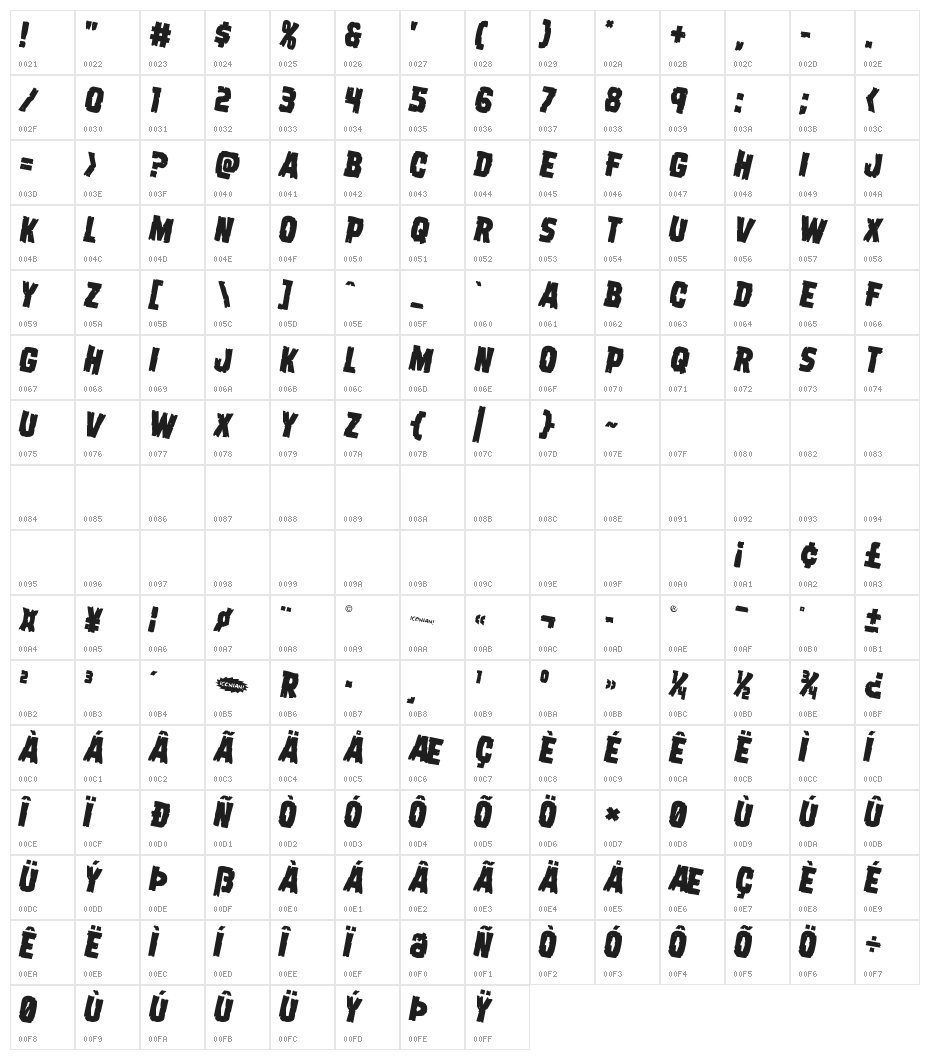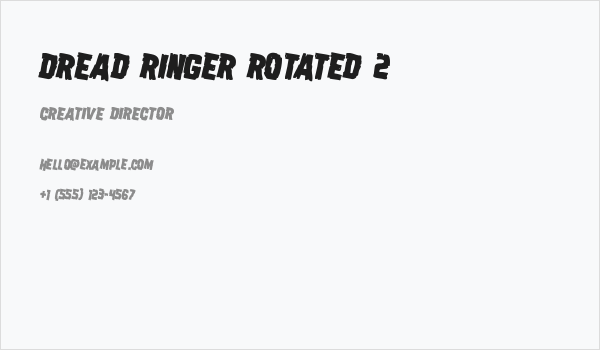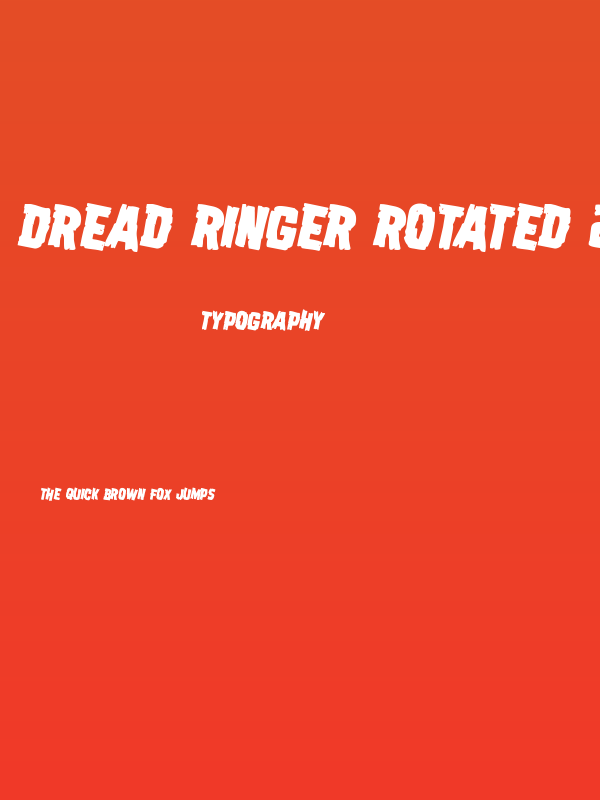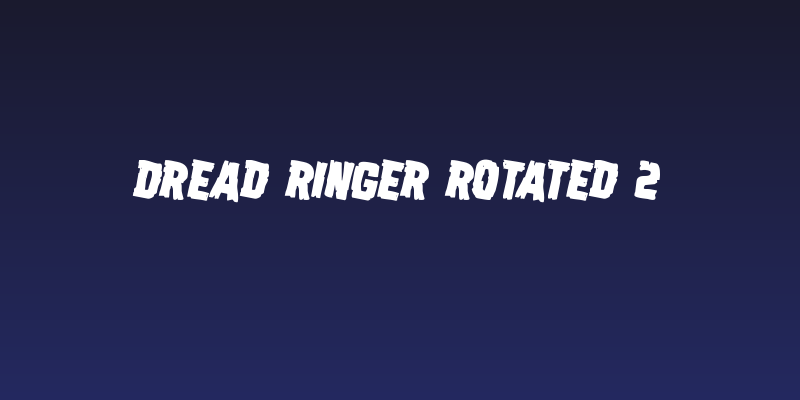
Dread Ringer Rotated 2 Font
| الفئات | Horror |
| النمط العام | Grunge, Energetic, Bold |
| مشاريع مقترحة | Ideal for posters, album covers, branding for edgy or alternative products, and any design requiring a bold, impactful statement. |